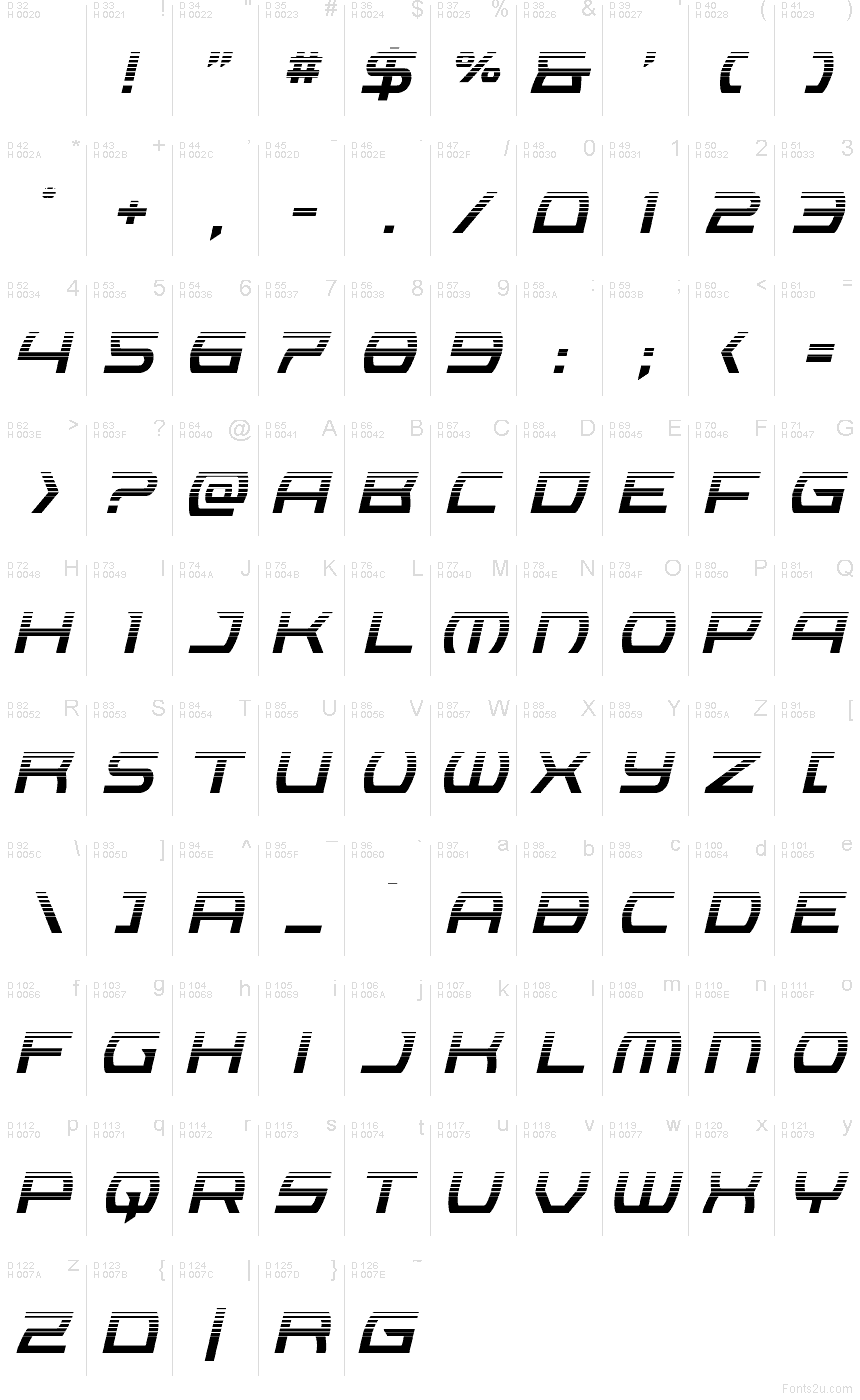
Icemaster Halftone Italic von Iconian Fonts ist eine kostenlose futuristische Halftone-Italic-Display-Schrift mit dem Flair eines Sci-Fi-Senders aus der Ära der Fernsehübertragungen. Die Buchstaben neigen sich nach vorne, geprägt durch breite, abgerundete Formen, die von sich wiederholenden horizontalen Streifen durchzogen sind. So wirkt das Alphabet aerodynamisch und eher elektronisch als kalt oder mechanisch.
Damit eignet sich diese Schrift natürlich perfekt für Spiele-Logos, Plakat-Titel, E-Sport-Branding, Mixtape-Cover und Titelkarten, bei denen eine kurze Zeile Dynamik direkt in die Buchstaben integrieren soll. Als kostenlose Schrift funktioniert sie auch hervorragend für Flyer von Tech-Events und markante Monogramme, besonders wenn die gestreiften Großbuchstaben Geschwindigkeit, Scans oder Signalstörungen vermitteln sollen.